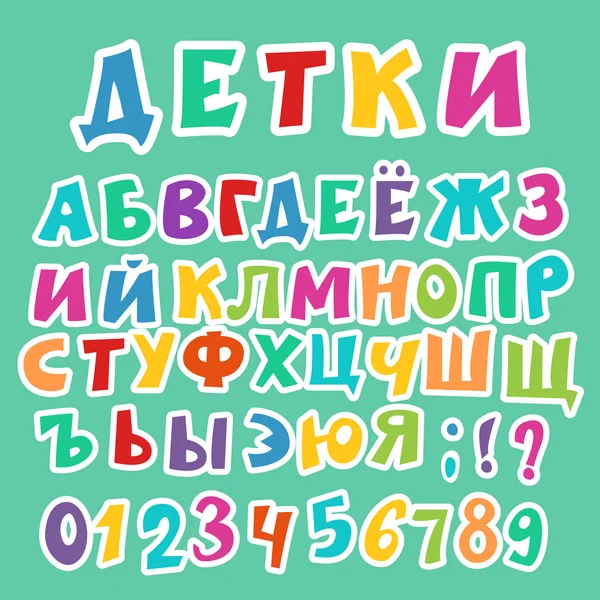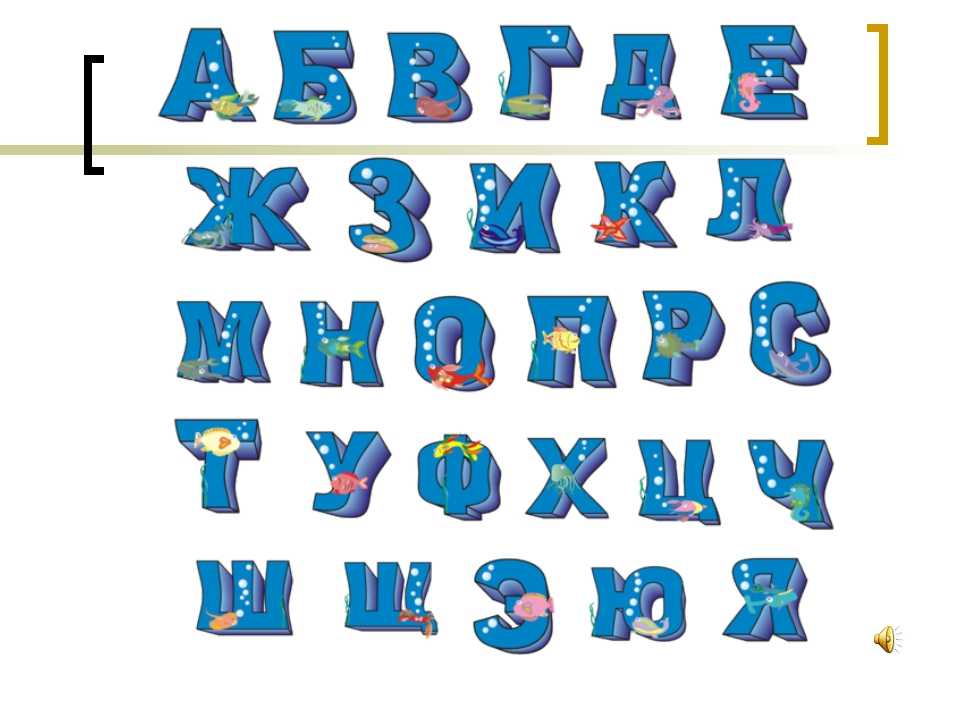
Детские шрифты для фотошопа. Русские шрифты из мультфильмов
Дети — самые суровые критики, если им что-то не нравится, они обязательно скажут об этом. В этом разделе очень много интересных, красивых шрифтов, ориентированных на детей.
Детские гарнитуры будут отличать вашу работу от многих других и обязательно порадуют юных потребителей. Важно помнить, что у детей состоятельные родители. Детским гарнитурам можно оформить книги, надписи на одежде или упаковку для игрушек.
Разве решится кто-то признаться, что он не любит мультики? Пожалуй, таких людей меньшинство. Посмотрите на детские шрифты нашего сайта. Если вас так и тянет улыбнуться, значит, в вас крепко сидят, воспоминая безмятежного детства и, дружно болтают ножками.
Мы подобрали для вас самые разные шрифты, как нового образца, так и проверенные временем. Ведь фантазия детей не знает границ. Они способны, не сходя с места, придумать массу интересных и забавных надписей. Только вглядитесь, в некоторых шрифтах каждая отдельная буква вмещает целый сюжет. Чего только не увидеть в детских шрифтах! Вот буквы дружно куда-то скачут, а здесь очень смешной почерк. Тут же небрежно написанный подростком заголовок.
Где можно использовать необычные шрифты ? Мультяшные символы прекрасно подходят для оформления книг, детских сайтов, открыток и для простых, забавных подписей. Детские шрифты неотделимы от происходящих событий в тексте. Это важно учитывать при выборе подходящего стиля. Также набор детских шрифтов с нашего сайта поможет привить интерес малыша к чтению.
Рисованный мультяшный кириллический шрифт
Классный веселый русский шрифт
Кириллический шрифт Disney
Жирный кириллический шрифт из мультика
Стильный рисованный мультяшный шрифт
Веселый жирный шрифт для титров мультика
Контурный мультяшный русский шрифт
Классный веселый кириллический шрифт
Контурный моноширинный мультяшный шрифт
Моноширинный мультяшный кириллический шрифт
Шрифт для титров в мультике
«Безалаберный» мультяшный кириллический шрифт
Русский шрифт из «Незнайка на луне»
Строгий, но веселый шрифт в кириллической раскладке
Тонкий мультяшный шрифт